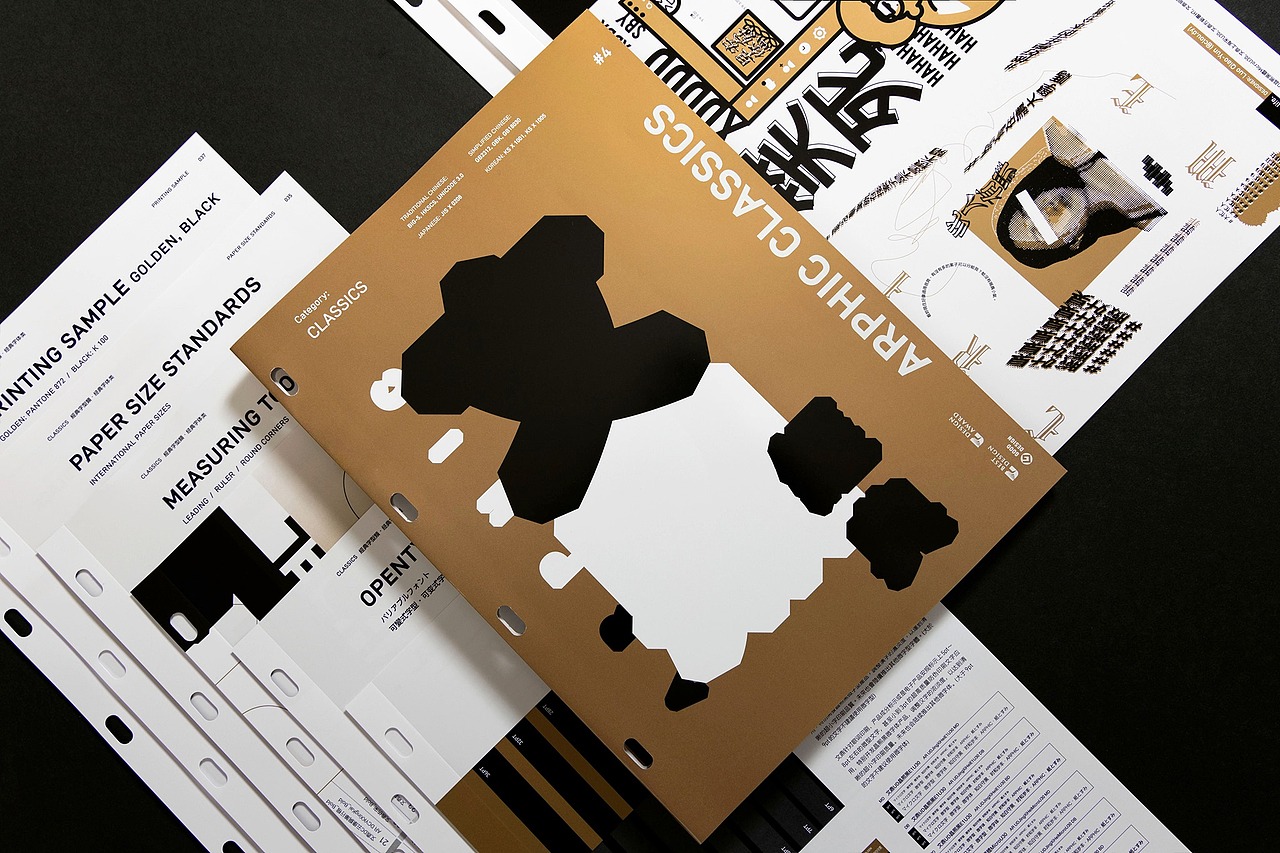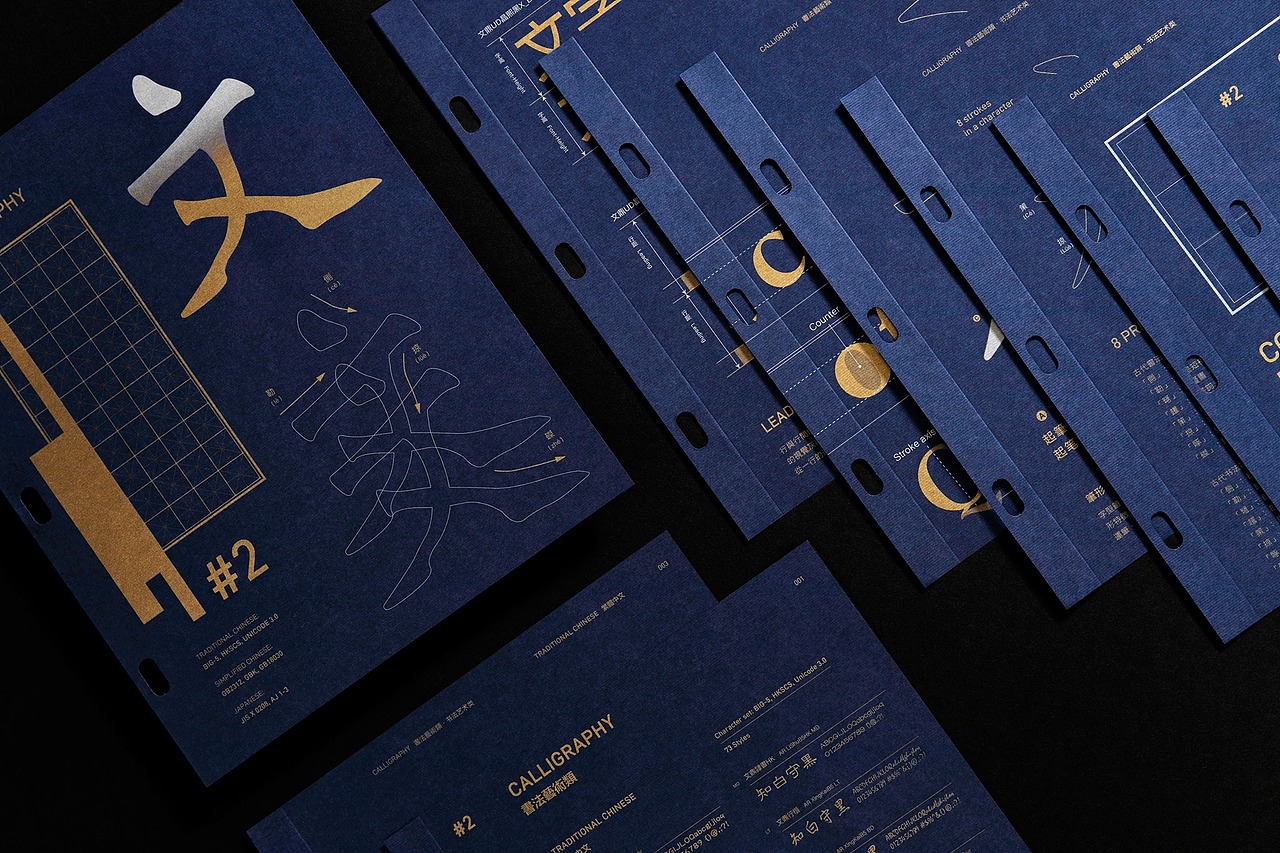
《2020文鼎字体册》荣获荷兰 2020 Indigo Award设计奖
《2020文鼎字体册》荣获荷兰 2020 Indigo Award 设计奖,分别是
Gold in Promotional Materials 2020|推广媒材金奖
Gold in Book Design 2020|书册设计金奖
Bronze in Digital Art 2020|数字艺术设计铜奖
我们特别与 Hong Da Design Studio合作,
重新规划改版《文鼎字体册》,完整收录了文鼎字型30年来近千套字体,将其分类成四类,分别为《经典字型类》、《书法艺术类》、《英欧文、复杂语系及合作字体类》、《装饰类》,并以各式尺寸组合成册,使用可拆式夹钉组装,呈现创意及设计感。
为了呈现字体本身不同的形式与样貌,我们特别邀请了16位设计师运用文鼎字型进行的设计创作,让不同类型的字体,透过设计师们巧思及创意,看见更多字体丰富的面貌。
此外《书法艺术类》,我们收录了许多中文字体相关知识,以及英欧文的字体部件、字符间距、行距、标点符号等等,期望帮助所有对字体有兴趣,想进一步了解相关知识的人,能灵活运用这些字体知识。
而《英欧文、复杂语系及合作字体类》及《装饰类》,我们尝试了各种字体在不同烫印效果中呈现更多元的字体样貌,以及将字符制作成贴纸使《文鼎字体册》本身更加生动有趣。